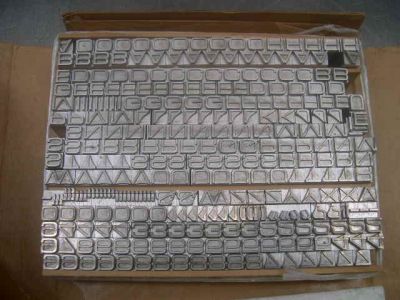
Fragen zum Zeichensatz der Microgramma
Kann mir jemand sagen, ob es die Microgramma:
auch als reinen Versalschnitt gibt? Ich habe etliche komplette und originalverpackte Schriftschnitte von der Schriftgießerei Nebiolo hereinbekommen. Das sind aber ausschließlich Versalien, Ziffern und Punkturen.
Kann es sein, daß es entweder auch einen reinen Versalschnitt gibt oder aber, daß die Gemeinen erst später, beim Digitalisieren zusätzlich entwickelt wurden?
ich hab irgendwo ein einzemuster der microgramma -
ich such es mal raus und schau ob es gemeine enthält.
ich hab irgendwo ein einzemuster der microgramma -
ich such es mal raus und schau ob es gemeine enthält.
Linotype zeigt halt auch die Gemeinen.
die microgramma wurde ursprünglich von aldo novarese für nebiolo erstellt. in der ersten fassung gab es nur versalien. da sie so populär wurde, kamen später noch minuskeln hinzu. und irgendwann wurde sie aus lizenzrechtlichen gründen in eurostile umgetauft, damit linotype sie auch im programm führen konnte. ich hab ein nebiolo specimen. die haben wirklich schöne dinge im programm gehabt.
dann brauch ich das muster ja nicht mehr suchen! hab
aber grad ein eurostile-muster von nebiolo gefunden!
Nike: Genau solche Informationen brauchte ich. So wird mir dieser Lettern-Bestand überhaupt erst klar und alles paßt zusammen: Diese Schriftenpakete sind bestimmt 25 Jahre alt. Der Schriften-Service Stempel bietet auch heute noch die Eurostyle als Bleisatz-Schrift an. Aber inklusiv der Gemeinen. Was ich tatsächlich nicht wußte, war, daß die Eurostyle aus der Microgramma entwickelt wurde und daß es diese - wie ich vermutete - zunächst nur als Versal-Schrift gab. Wieder etwas dazu gelernt. Ich hatte schon befürchtet, daß die Pakete mit den Gemeinen verlorengegangen seien.